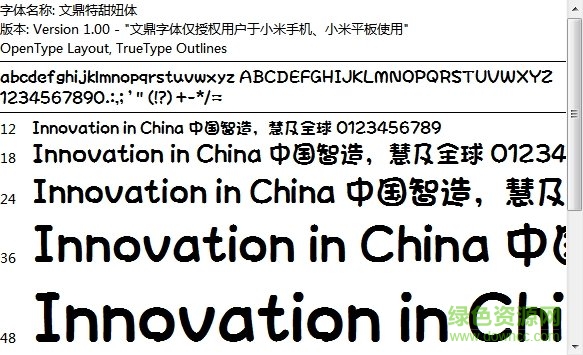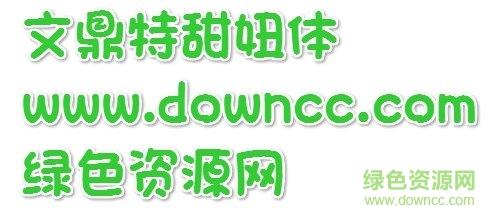
文鼎特甜妞體字體
文鼎特甜妞體是文鼎甜妞系列字體中最大最粗黑的卡通字體,整體風(fēng)格其他兩款甜妞字體類似,在構(gòu)造上更顯大氣深沉,極容易抓住大家的眼光和注意力,來綠色資源網(wǎng)即可免費(fèi)體驗(yàn)!
文鼎特甜妞字體介紹
文鼎特甜妞體是一款卡通POP風(fēng)格的藝術(shù)字體,字形活潑可愛,充滿孩童般童趣的天真氣息,可用于廣告設(shè)計(jì)字體、網(wǎng)頁設(shè)計(jì)字體、包裝設(shè)計(jì)字體、 屏幕顯示字體等。
文鼎特甜妞體外形漂亮、效果出眾,且結(jié)構(gòu)清晰,風(fēng)格統(tǒng)一,圓潤地可愛,像個(gè)小甜妞而命名,字庫完整不缺字,讓你的設(shè)計(jì)更有活潑生機(jī),用在兒童內(nèi)容的設(shè)計(jì)上非常不錯(cuò)!